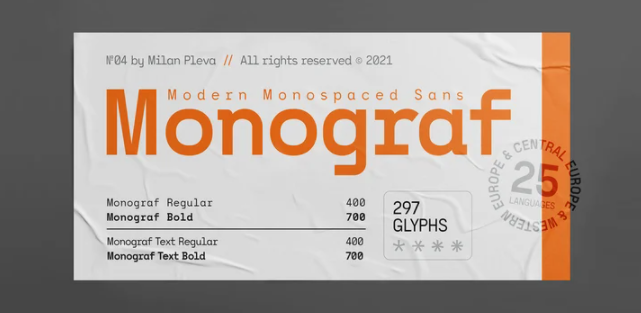
[Myfonts] Monograf Font (2021)
Monograf изначально был разработан как моноширинный шрифт фиксированной ширины, имеющий 2 начертания (Regular и Bold). Monograf Text - это производный стиль Monograf с пропорциональным интервалом и хорошо сбалансированным кернингом, чтобы текст легче читался и выглядел оптически сбалансированным.
Таким образом, в общем пакете вы получаете 4 части этого шрифта: Monograf Regular, Monograf Bold, Monograf Text Regular и Monograf Text Bold.
Этот универсальный шрифт с чистой геометрией и слегка закругленными угловыми элементами отлично работает как в цифровом пространстве, так и в печати. Он также сохраняет свою читаемость при меньших размерах. Типографические особенности включают цифры старого стиля, направленные стрелки и четыре вида звездочек. Весь шрифт подходит для таких целей, как табличная верстка, кодирование, веб-сайт, а также для журналов, логотипов, вывесок, продукции и других.